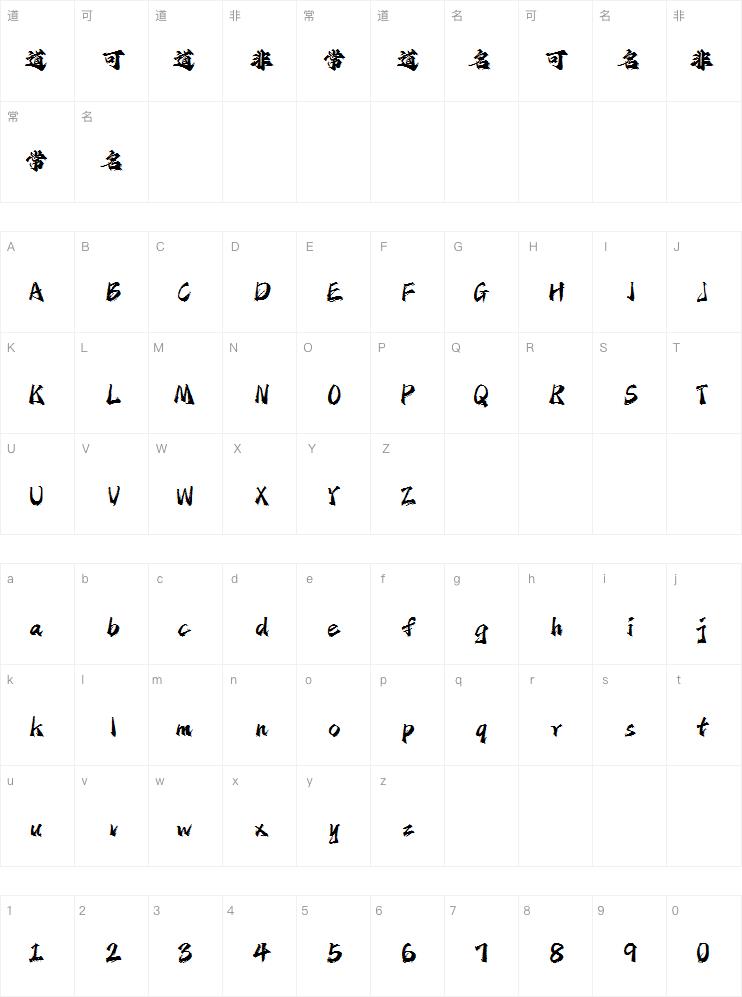
字魂北京民艺非遗研究院体,是字魂为北京民艺非物质文化遗产研究院打造的定制字体。以文房四宝代表的毛笔书写为出发点,在手书笔型中保留了自然笔锋变化与墨韵效果,使字体整体呈现出古朴气质。部分笔画进行了适度地伸展、变形,用一种非完全规整的灵动,赋予字体龙狮舞动的洒脱之感,以此呼应研究院推动非遗文化随时代与潮流共同发展的开放态度。该字体适用于影视、文创、文化宣传等场景。